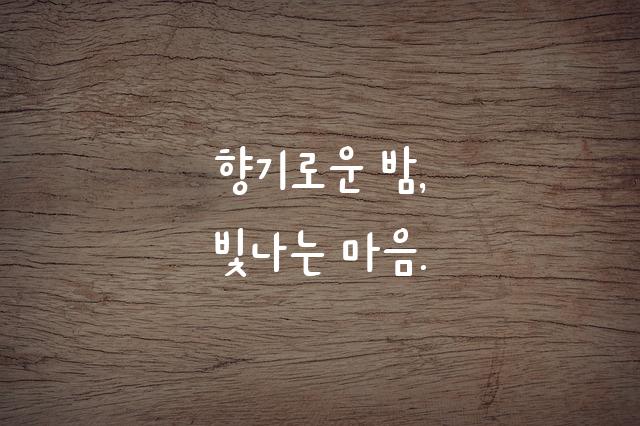
상주곶감체는 동글동글한 제목용 둥근 고딕 폰트로, 상주시청과 투게더그룹이 제작한 폰트입니다. 따뜻하고 친근한 느낌을 전달하며, 시각적으로 매력적인 디자인을 자랑합니다.
상주곶감체은(는)
기본 고딕, 둥근 스타일, 감성적인, 자연감성, 부드러움, 복실복실, 길고/크고 계열의 생김새를 가지고 있으며
포스터, 웹/앱 디자인, 초대장 등에서 자주 활용되며, 효과적인 메시지 전달에 적합합니다.
이 폰트는 크리에이티브, 라이프스타일, 문화/예술 분야에 잘 어울리며,
친근한, 감성적인, 편안한 느낌을 담고 있는 것이 특징입니다.